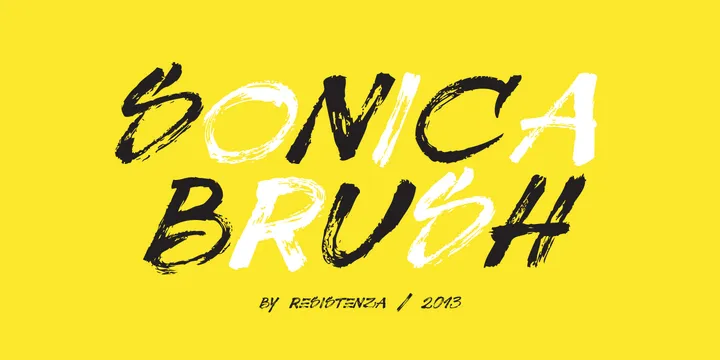
A Sonica Brush Font é uma escolha perfeita para quem busca uma fonte elegante e versátil para criar designs modernos e sofisticados. Seu design delicado e suave oferece um toque de brilho à sua obra, seja em layout de newsletters ou criação de sites. Inspirada na natureza, a Sonica Brush captura os movimentos fluidos e sutis que encontramos nos rascunhos naturais. Este estilo brush traz consigo uma atmosfera fresca e criativa ao seu trabalho, tornando-a perfeita para um gosto contemporâneo. A Sonica Brush é projetada por Hamilton, designer talentoso que transformou sua arte na fonte ideal para quem valoriza a simplicidade de linhas fluidas e detalhes meticulosos. Se você está buscando uma fonte brush moderna que ressoa com o seu gosto pessoal, a Sonica Brush é uma excelente escolha. Suavemente brilhante e repleta de vida natural, ela complementará perfeitamente qualquer projeto gráfico que você estiver criando. Aproveite para experimentar as nuances e sutilezas desta fonte, e veja como ela pode transformar seus designs em algo único e sofisticado.